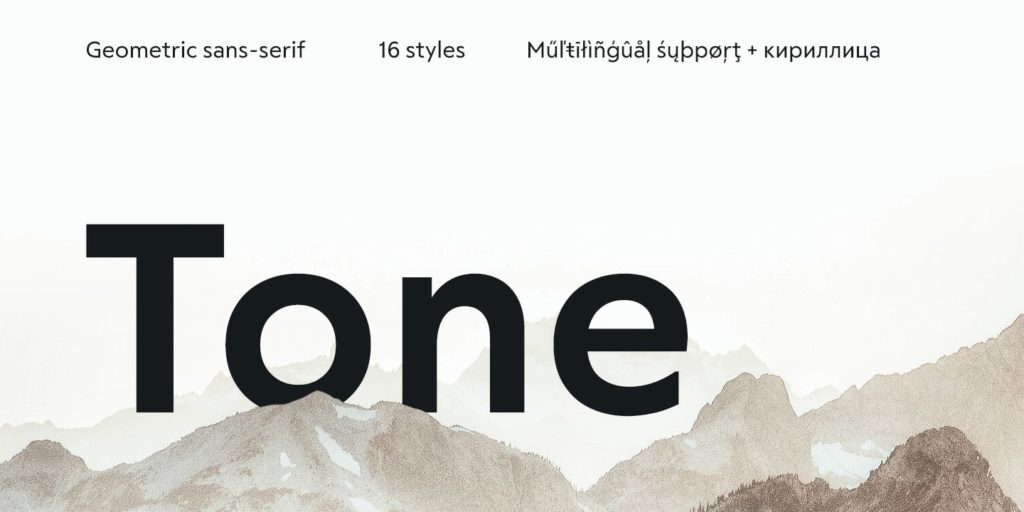
Шрифт RF Tone
Это современный геометрический гротеск, разработанный дизайнером Мишей Панфиловым (Misha Panfilov). Вдохновленный классическими образцами начала XX века, он был адаптирован под современные требования типографики и цифровых экранов. Отличается строгими формами, идеальными кругами в основе букв и широкой гарнитурой из 16 начертаний — от тончайшего Ultralight до массивного Black. Этот кириллический шрифт отлично подходит для создания смелых заголовков, логотипов и фирменного стиля. Вы можете скачать бесплатно файлы с примерами начертания на нашем сайте